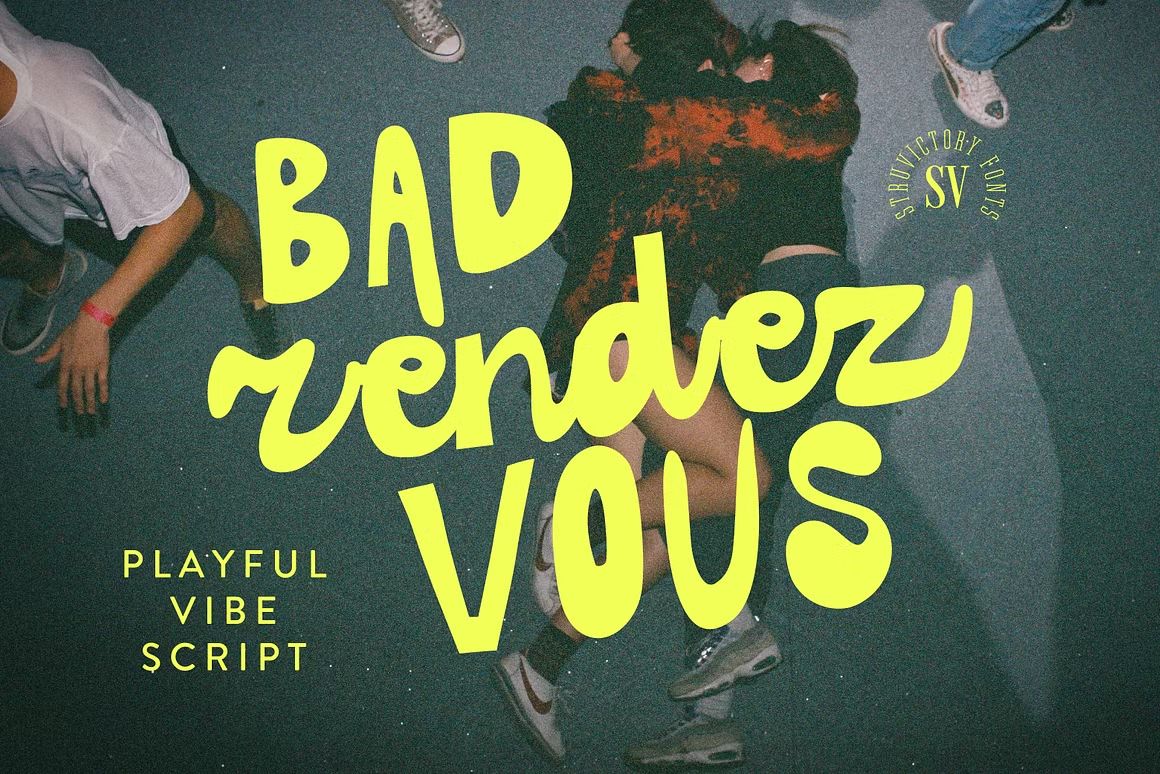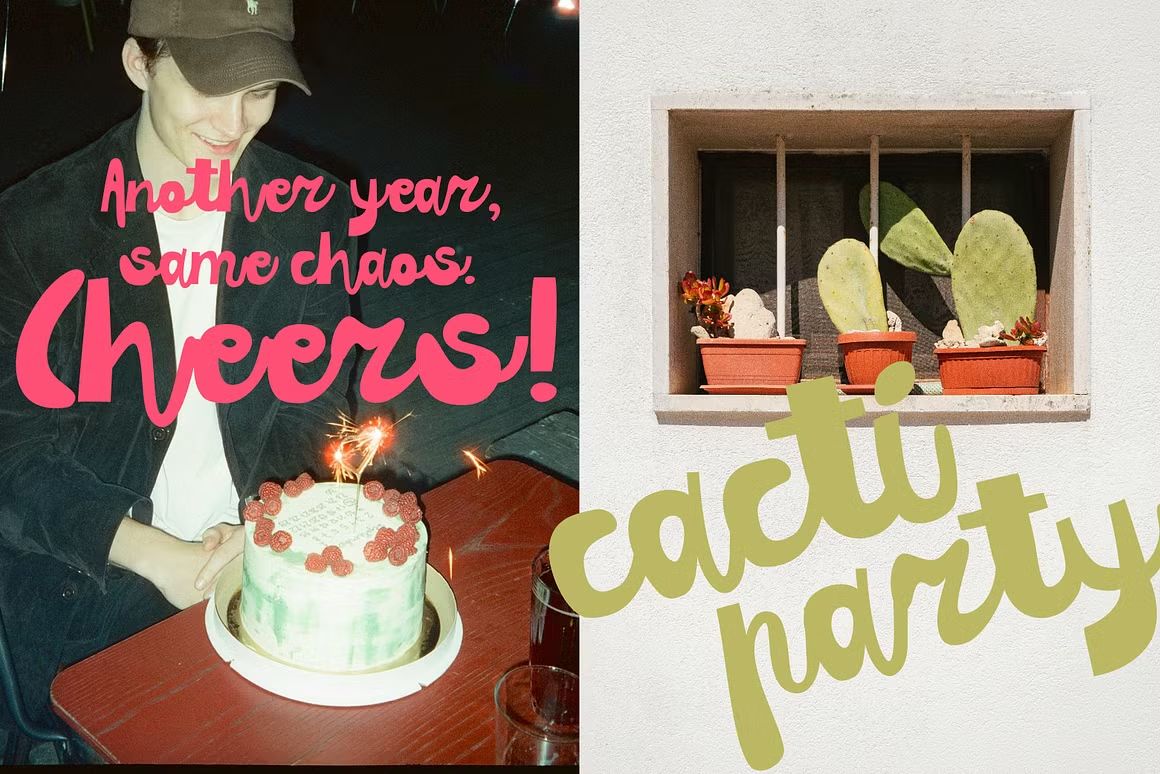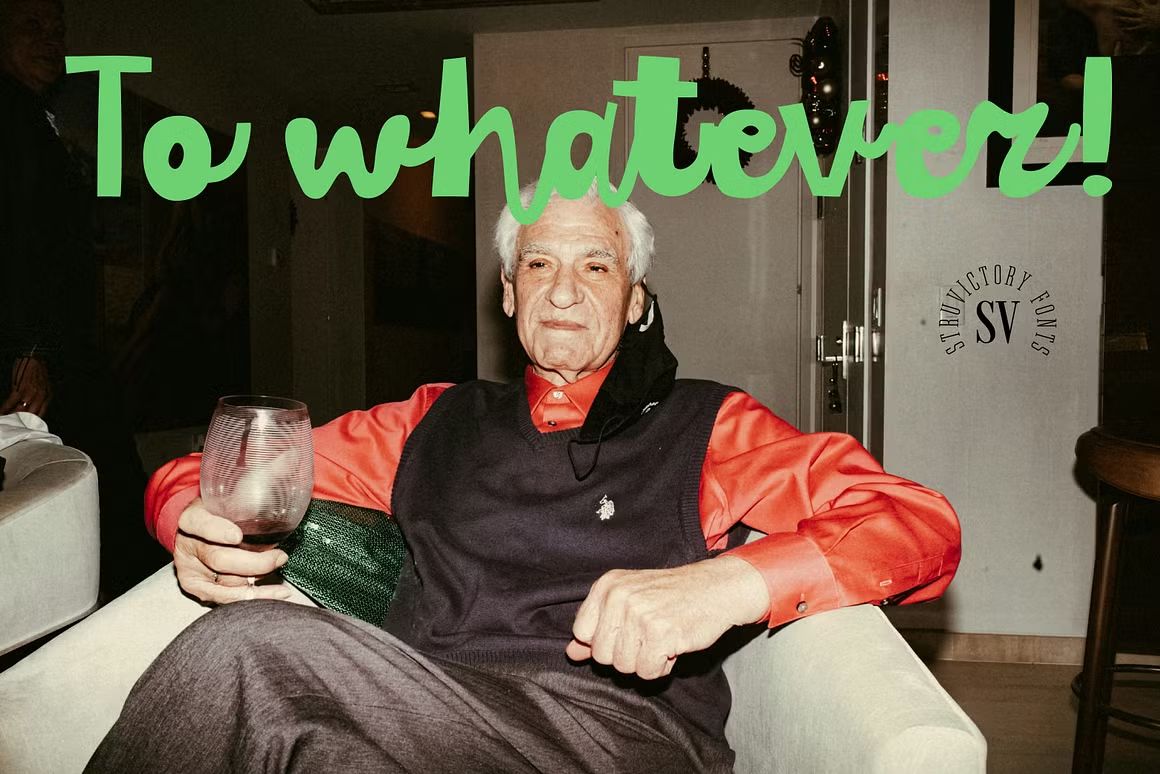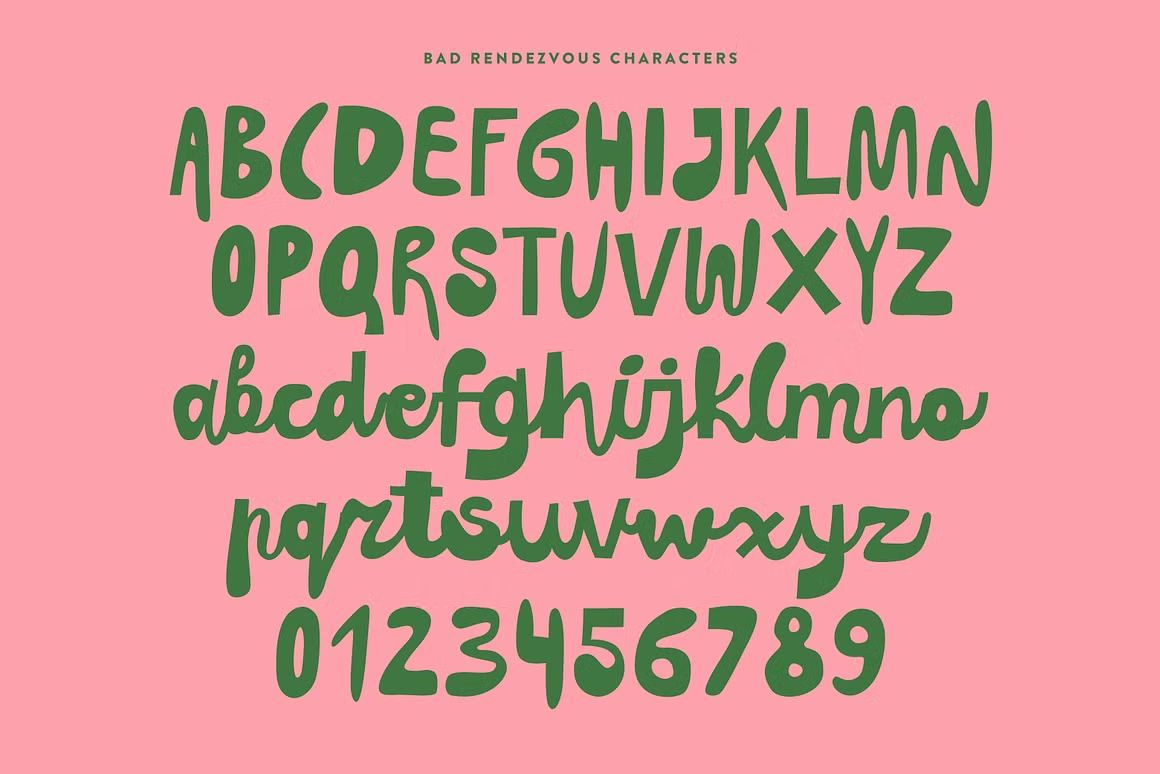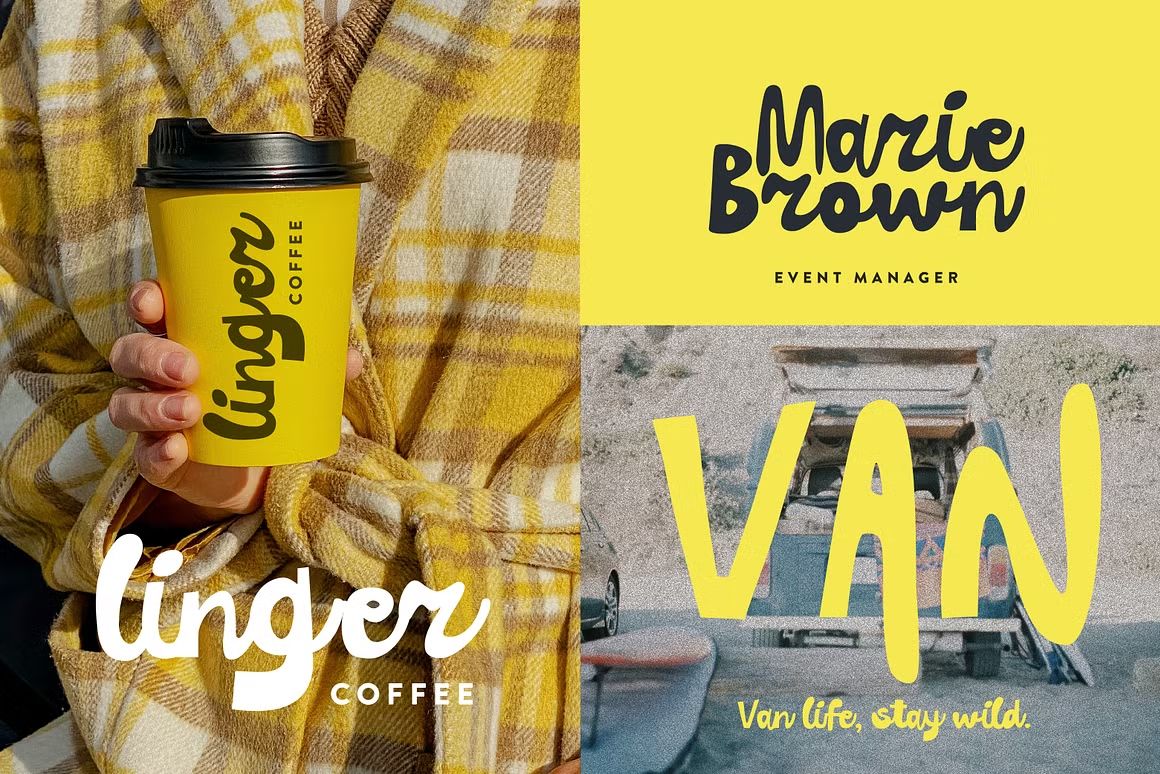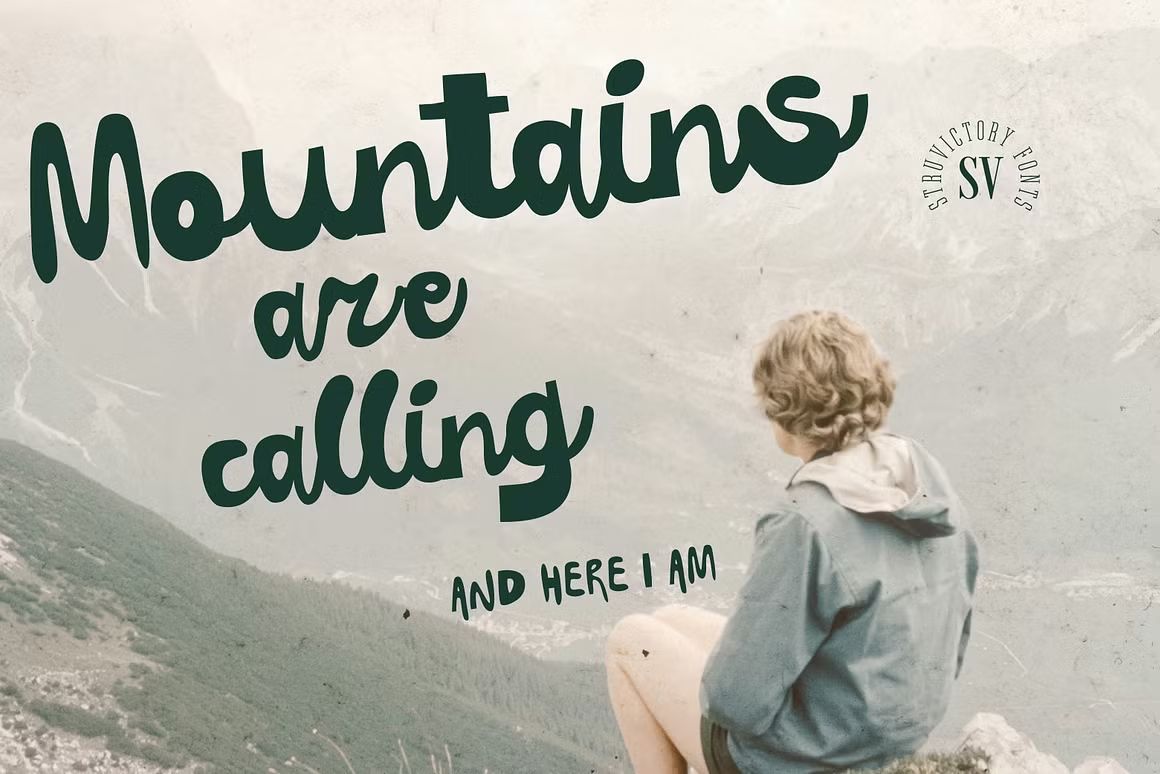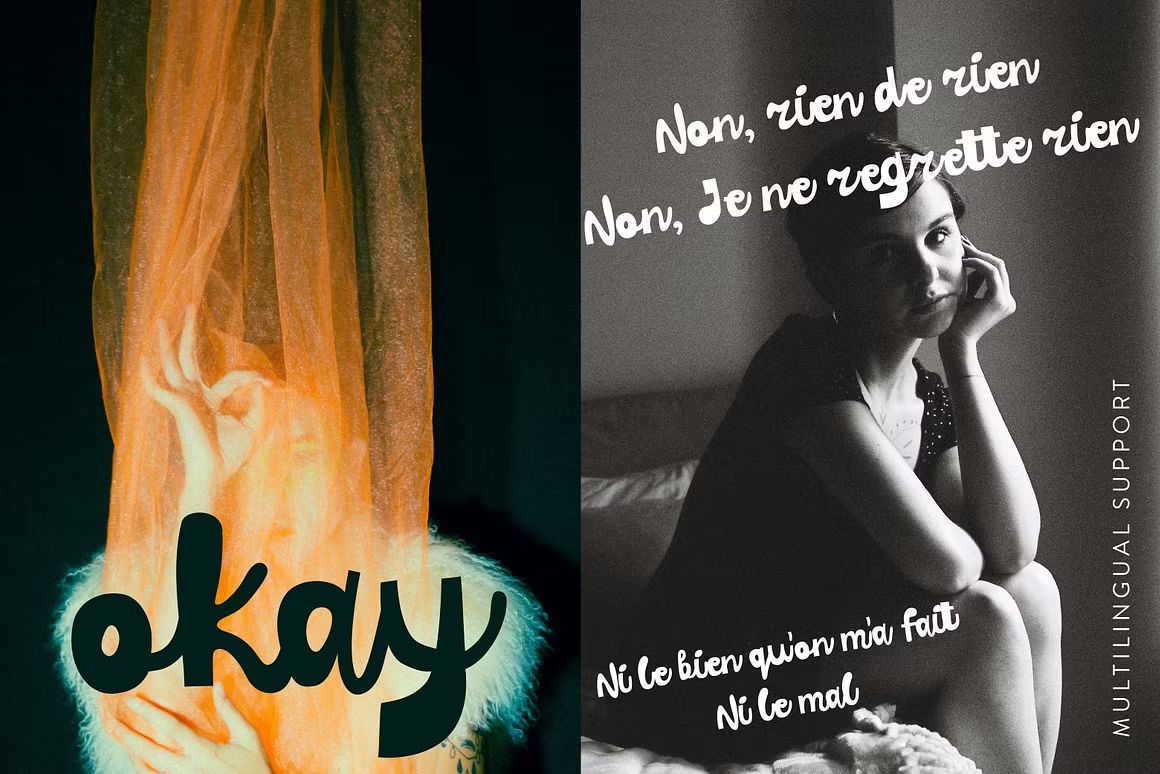
Bad Rendezvous – Script Font
Bad Rendezvous adalah font script tebal bergaya tulisan tangan ekspresif, cocok untuk desain berani dan kreatif. Format OTF/TTF/WOFF, siap digunakan di berbagai proyek visual.
Bad Rendezvous adalah font script dengan gaya tulisan tangan yang bold, ekspresif, dan penuh karakter. Font ini cocok untuk desain yang ingin tampil berani dan emosional, seperti poster, cover album, branding alternatif, kutipan, atau konten media sosial yang edgy dan artistik. Dengan sapuan kuas yang dinamis dan lekukan tegas, Bad Rendezvous menghadirkan kesan rebel namun tetap estetis.
• Gaya script tebal dan ekspresif dengan sapuan kuas
• Cocok untuk poster, branding alternatif, dan desain kreatif
• Termasuk huruf besar, kecil, angka, simbol, dan ligatur